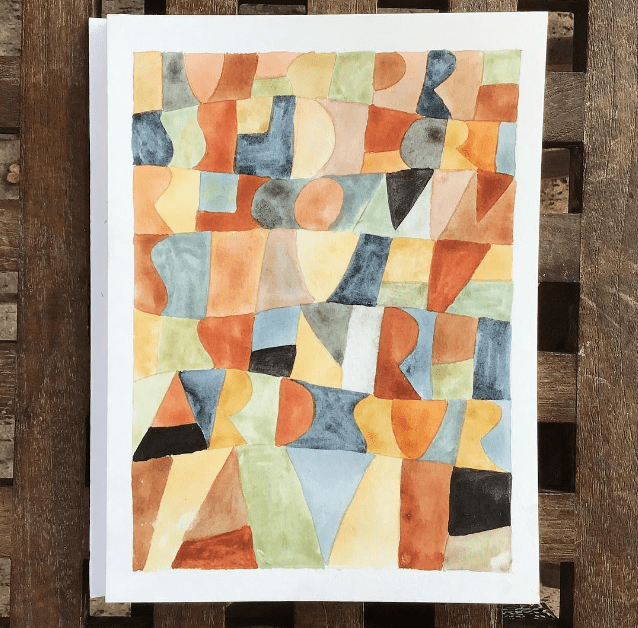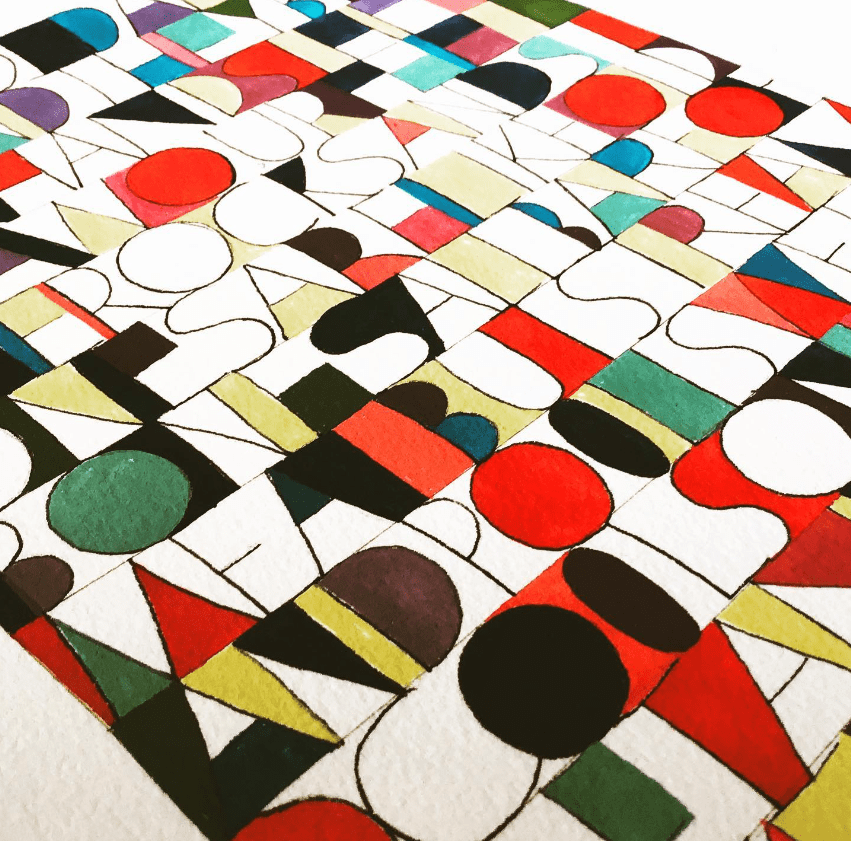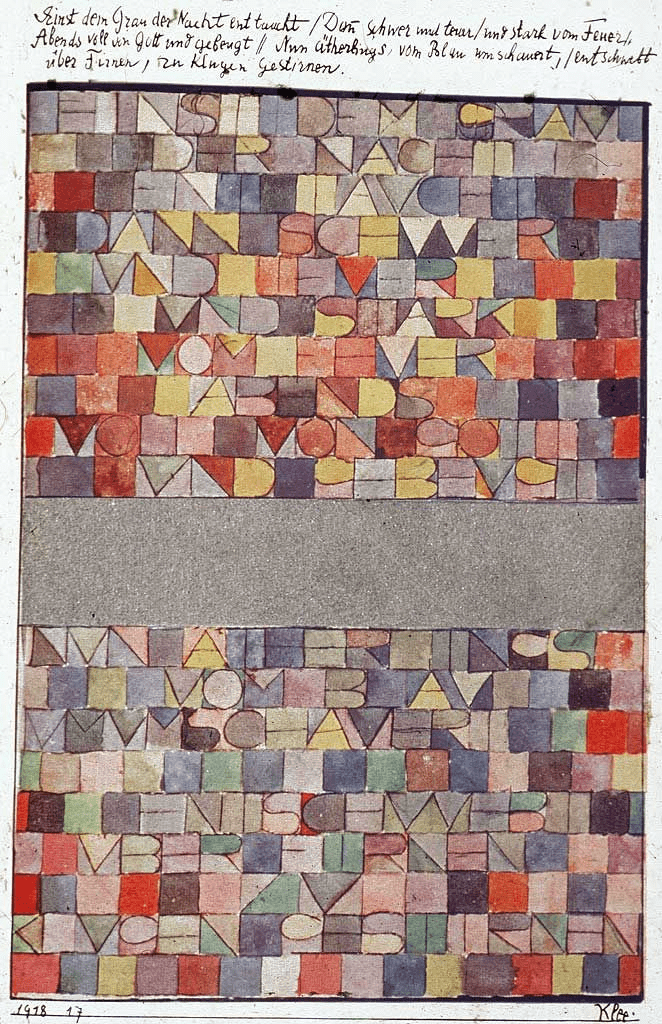
Aujourd’hui je vous propose de partir de l’une des oeuvres les plus célèbres de Paul Klee : « Jadis surgit du gris de la nuit », créée en 1918. Parmi les « jeux de lettres« , c’est un de mes favoris !
Quelques mots sur Paul Klee et sur ses damiers colorés
Paul Klee est un artiste suisse du XXe siècle qui a influencé de nombreux artistes modernes. Il est surtout connu pour ses peintures abstraites et ses aquarelles, qui utilisent des couleurs vibrantes et des formes géométriques pour créer des œuvres d’art uniques et expressives. Klee était un artiste très intuitif, et il croyait que l’art devait être créé à partir de la spontanéité et de l’émotion plutôt que d’être planifié et exécuté selon un plan rigide. Dans « Jadis surgi du gris de la nuit », on peut voir cette qualité dans les formes fluides et les couleurs douces qui créent une atmosphère onirique.
Jadis surgit du gris de la nuit – Paul Klee – 1918
Cette oeuvre est fréquemment proposée dans les programmes d’arts visuels, dès l’école primaire. La géométrie simple des carrés pavés associée à des lettres capitales est en effet facile à recréer pour des enfants – ou des grands ! La mise en couleur est elle aussi relativement simple, puisqu’il « suffit », a priori, de colorier dans les formes, de manière intuitive, sans règles préalables. En observant de plus près, on voit que ce jeu a priori aléatoire s’équilibre d’une certaine façon, que les couleurs se répondent et que le texte se fond dedans. Dans d’autres oeuvres de Klee, on observera des séquences de couleurs, qui guideront le regard.
Pour le spectateur, l’œil sera spontanément attiré vers les couleurs et le chemin qu’elles proposent, ou sera attiré par le déchiffrement du texte.
Quelques réalisations, à la manière de Paul Klee
Le premier lettrage que j’ai fait, inspiré du travail de Paul Klee, était dans un carnet, pour me vider la tête et utiliser une fin de palette. Dans la foulée j’en ai fait d’autres, sur du bon papier, à la gouache ou à l’aquarelle.
Poser la couleur est une vraie méditation; Au départ on y va un peu au pif, puis une sorte de cheminement se met en place, conscient mais non réfléchi (si je vous ai perdu, désolée ah ah !). Ce faisant, écouter une bonne musique bien planante est un must pour se laisser totalement glisser hors du temps.
Comme pour les jeux d’écriture, on peut y aller de ses variations :
• contrasté ou fondu
• garder ou pas une part de lisibilité
• imprimer un chemin avec la couleur… ou pas
• travailler en camaïeux, avec des couleurs complémentaires
Au final, j’aime l’idée que le texte disparaisse, mais pas totalement. J’aime ce travail de la couleur, et l’éventuel rythme qui se crée sur le damier. J’aime aussi les petites histoires qui se créent, via les couleurs qui se côtoient à différents endroits du tableau. C’est presque un super exercice de nuancier !
Maintenant, à vous de jouer !